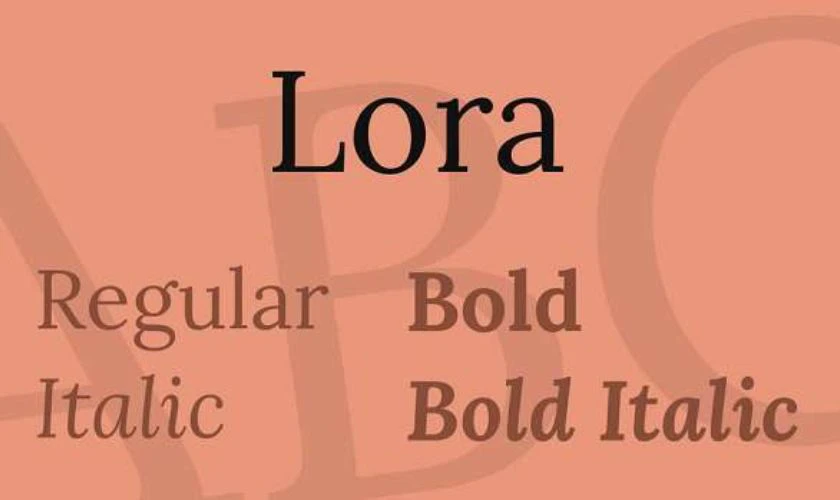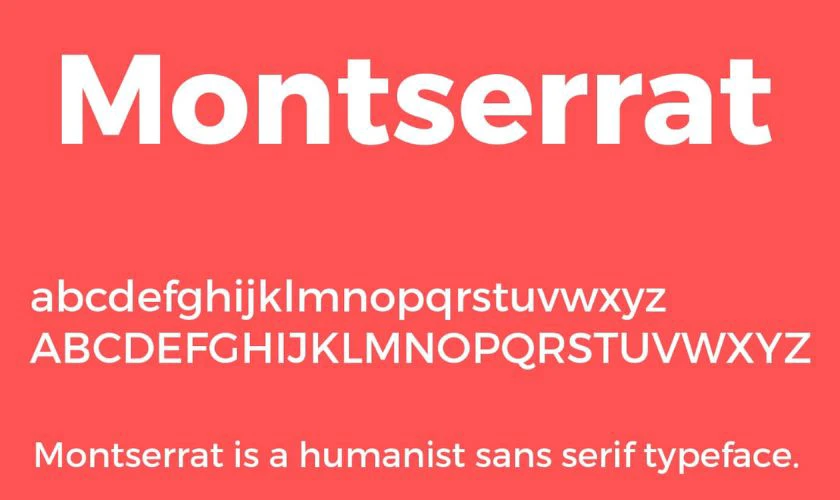
10.000+ Font chữ đẹp tiếng Việt được ưa chuộng 2026
Font chữ đẹp giúp nâng tầm thiết kế, mang đến sự sáng tạo và chuyên nghiệp cho mọi dự án. Nếu bạn đang tìm kiếm các font chữ đẹp tiếng Việt, bài viết này sẽ giới thiệu hơn 10.000+ lựa chọn phù hợp. Ngoài ra, bạn cũng có thể tự tạo font chữ đẹp theo phong cách riêng. Cùng khám phá ngay ở bài viết sau nhé!
Font chữ đẹp không chỉ là một yếu tố thẩm mỹ mà còn mang lại nhiều lợi ích quan trọng trong thiết kế và truyền thông. Dưới đây là một số lợi ích chính mà các font chữ đẹp có thể mang lại:
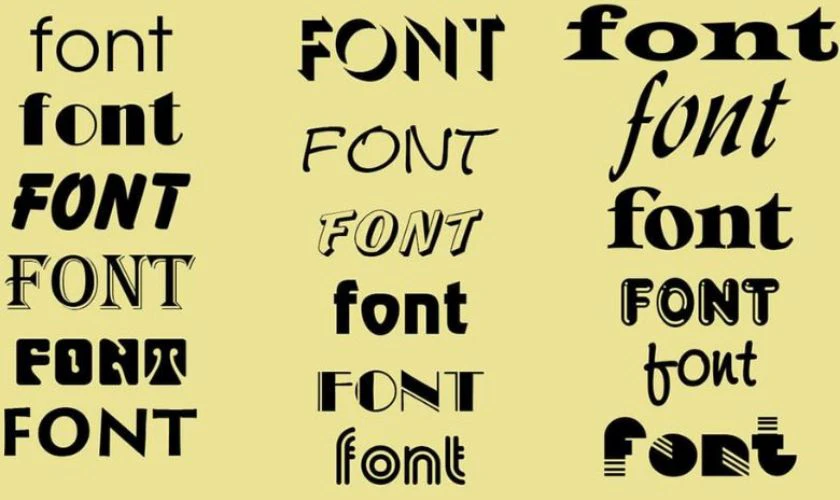
Font chữ đẹp tiếng Việt không chỉ là yếu tố trang trí. Đây còn là một công cụ mạnh mẽ để truyền tải thông điệp, tạo ấn tượng và xây dựng thương hiệu. Việc lựa chọn font chữ phù hợp là rất quan trọng để đạt được hiệu quả trong thiết kế và truyền thông.
Trong 2026, nhiều font chữ đẹp đã trở thành lựa chọn của các nhà thiết kế và người sáng tạo nội dung. Những font chữ này không chỉ phù hợp với nhiều dự án khác nhau. Chúng còn mang đến phong cách và sự tinh tế cho các sản phẩm thiết kế. Dưới đây là danh sách 10 font chữ đẹp được ưa chuộng nhất:
Times New Roman là một trong những font chữ kinh điển và phổ biến nhất thế giới. Được phát triển vào năm 1932, font này có thiết kế serif mang lại cảm giác trang trọng và nghiêm túc. Với sự dễ đọc và độ chính xác cao, đây vẫn là lựa chọn trong các tác phẩm văn học và báo chí.
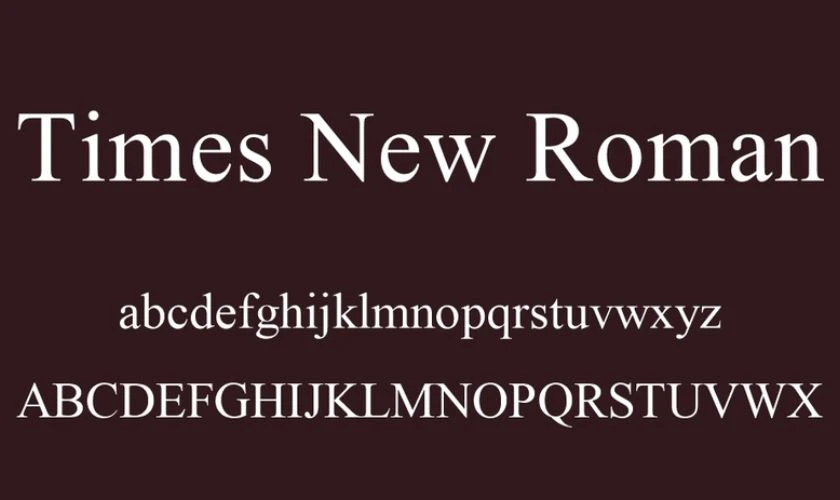
Với sự đơn giản và dễ tiếp cận, Times New Roman còn là một font mặc định. Đặc biệt dùng trong việc soạn thảo văn bản khi vào Microsoft Word. Đây là một lựa chọn lý tưởng khi bạn cần truyền tải thông điệp rõ ràng và dễ dàng hiểu được.
Arial là font chữ đẹp sans-serif được phát triển với mục đích thay thế cho Helvetica. Tuy nhiên font này lại mang đậm đặc trưng riêng với đường nét thẳng và đơn giản. Arial có tính ứng dụng cao và thường xuất hiện trong tài liệu văn phòng, website, thiết kế đồ họa,... Arial là sự lựa chọn lý tưởng khi bạn cần sự rõ ràng, đơn giản nhưng vẫn nổi bật.
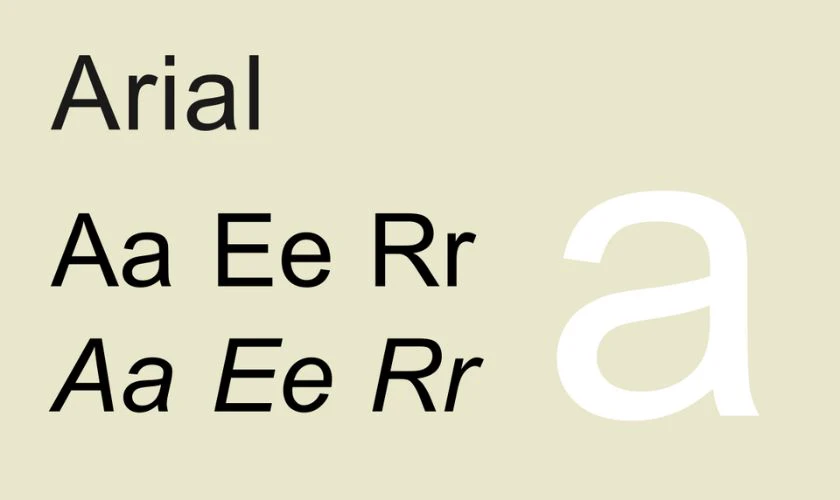
Arial đặc biệt hữu ích trong các thiết kế yêu cầu sự tối giản và dễ đọc trên nền tảng kỹ thuật số. Vì vậy, nó trở thành font chữ chủ đạo trong nhiều website và giao diện người dùng, giúp tăng khả năng tiếp cận và thu hút người xem.
Roboto là một trong những font chữ sans-serif phổ biến và hiện đại. Đặc biệt được sử dụng rộng rãi trong các ứng dụng di động và website. Font này được thiết kế với các đường nét mượt mà, giúp tạo ra sự hòa hợp tinh tế. Các ký tự trong Roboto được thiết kế để tối ưu hóa trải nghiệm và người dùng dễ theo dõi nội dung.
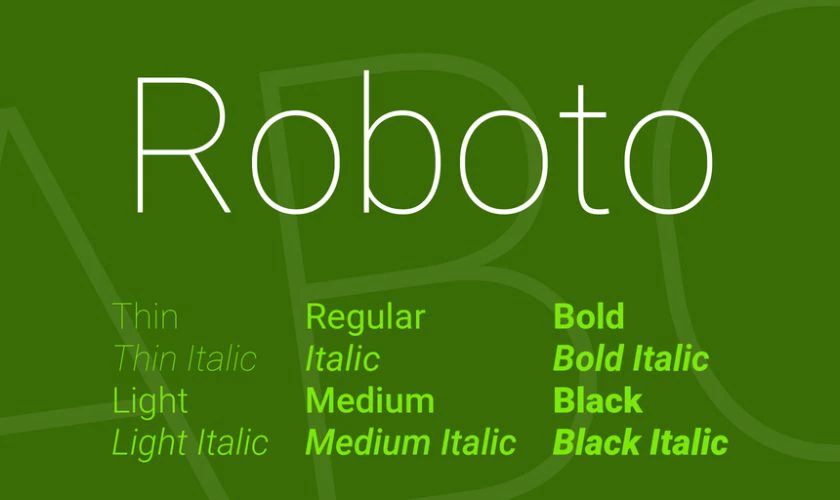
Roboto mang đến sự linh hoạt và dễ đọc, đặc biệt khi sử dụng cho các thiết kế trực tuyến. Đây là một trong những font chữ được yêu thích trong các dự án thiết kế web, quảng cáo,...
Helvetica là một font chữ sans-serif nổi tiếng với thiết kế đơn giản nhưng vô cùng mạnh mẽ. Với các đường nét cân đối, Helvetica không chỉ dễ đọc mà còn mang lại cảm giác chuyên nghiệp. Font khá thích hợp cho các thiết kế yêu cầu tính hiện đại và tinh tế. Helvetica là sự lựa chọn phổ biến trong ngành quảng cáo và thương hiệu.
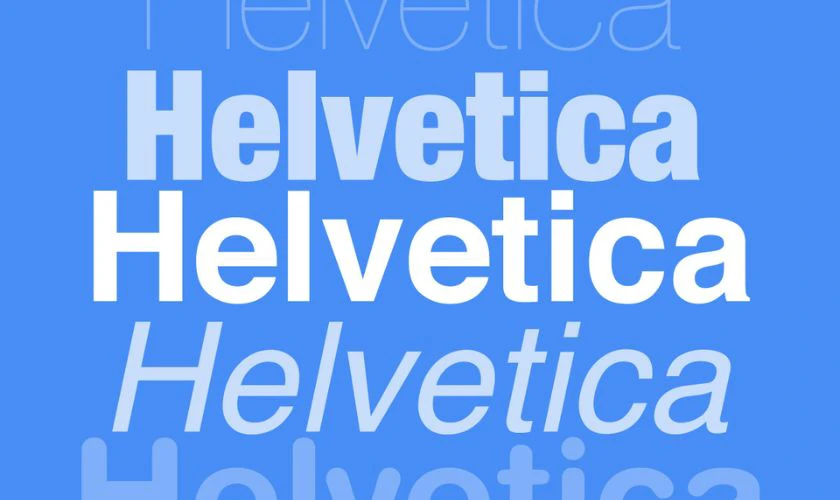
Sự đặc biệt của Helvetica là nó có thể dễ dàng sử dụng trong mọi loại hình thiết kế. Từ tài liệu in ấn cho đến các trang web. Font chữ tạo ra một ấn tượng mạnh mẽ, giữ được sự đơn giản nhưng không thiếu phần sang trọng.
Open Sans là font chữ đẹp sans-serif được thiết kế để dễ đọc và dễ tiếp cận trên màn hình. Đặc biệt là trong các giao diện web và ứng dụng di động. Font này có các đường nét nhẹ nhàng, cân đối, giúp người đọc dễ dàng nắm bắt thông tin. Open Sans rất phù hợp cho các thiết kế đòi hỏi sự dễ dàng tiếp cận và sử dụng lâu dài.
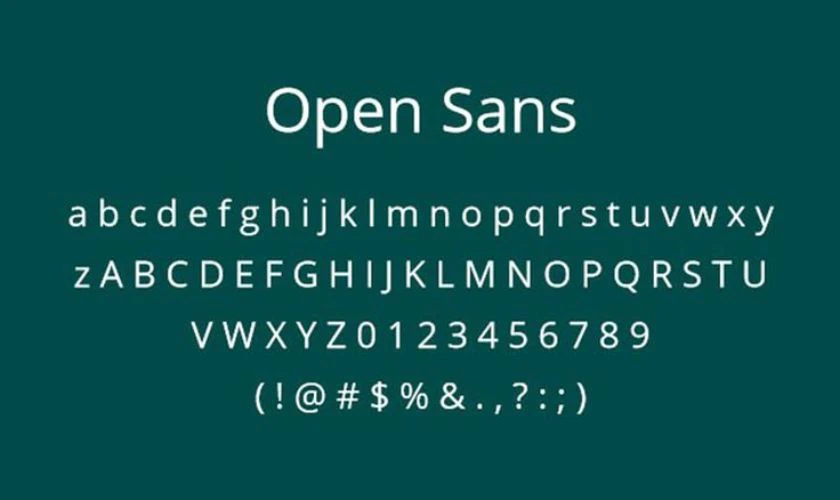
Với sự tối giản và tính ứng dụng cao, Open Sans thường được sử dụng trong các giao diện người dùng. Tài liệu trực tuyến và các nền tảng có lượng truy cập lớn. Đây là một trong những font chữ phổ biến cho các thiết kế hiện đại.
Verdana là một font chữ sans-serif được thiết kế bởi Matthew Carter cho Microsoft. Font được tạo ra để dễ đọc trên màn hình, với các ký tự rõ ràng và khoảng cách rộng rãi. Verdana trở thành sự lựa chọn lý tưởng cho website, ứng dụng di động và các tài liệu điện tử. Đương nhiên Verdana hiển thị rõ ràng ngay cả ở kích thước nhỏ.
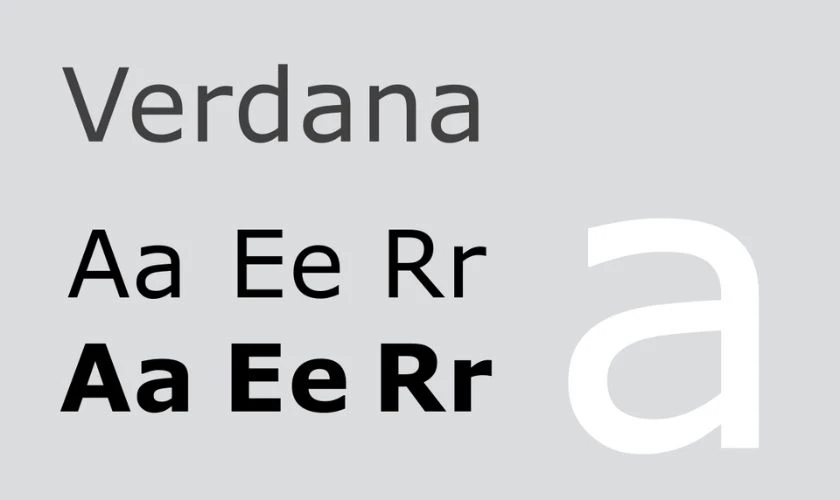
Font chữ này được biết đến vì tính khả dụng cao trên các nền tảng kỹ thuật số. Đây cũng là một trong những lựa chọn đầu tiên cho thiết kế giao diện người dùng và văn bản trực tuyến. Nếu bạn đang tìm một font chữ đẹp và được ưa chuộng thì có thể chọn Verdana.
Courier New là một font chữ monospace được thiết kế bởi Adrian Frutiger cho IBM. Font được dựa trên các font chữ máy đánh chữ, với các ký tự có chiều rộng bằng nhau. Courier New thường được sử dụng trong lập trình, soạn thảo văn bản và các ứng dụng kỹ thuật.
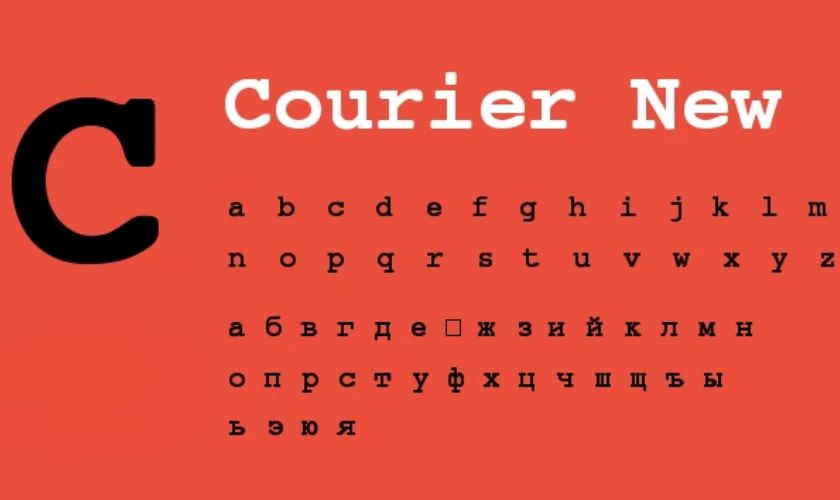
Courier New mang đến cảm giác cổ điển, chuyên nghiệp và rõ ràng. Đây là một lựa chọn lý tưởng cho các nội dung kỹ thuật, tác phẩm văn học, kịch bản phim,... Nơi tính chính xác và dễ đọc là yếu tố quan trọng.